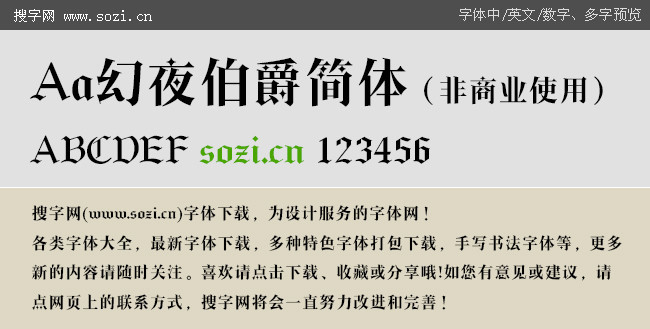
Aa幻夜伯爵簡體(非商業(yè)使用)
搜字網(wǎng)給大家提供一款A(yù)a幻夜伯爵簡體(非商業(yè)使用)中文字體下載,Aa幻夜伯爵簡體是一款哥特風(fēng)格的中文個性藝術(shù)字體,充滿了神秘感,適合海報設(shè)計、包裝畫冊、游戲宣傳等廣告應(yīng)用(此字體為個人非商用版,商用可以聯(lián)系QQ:1006760504)。